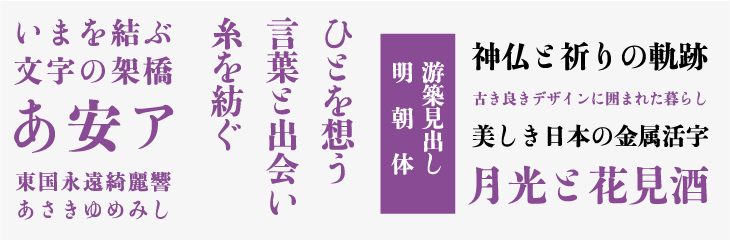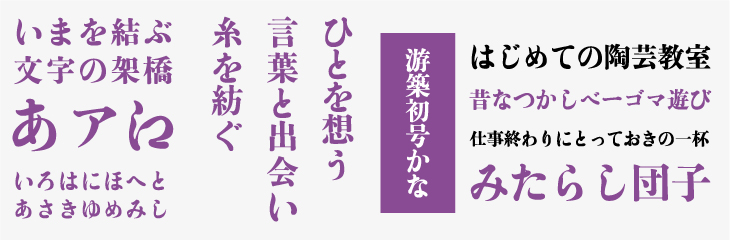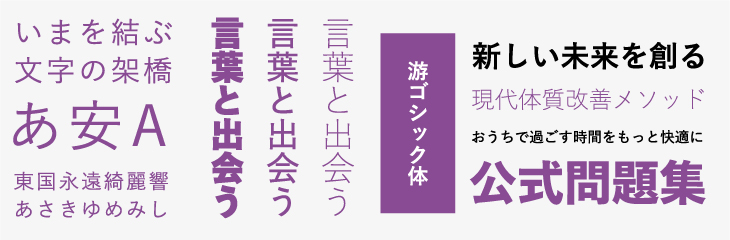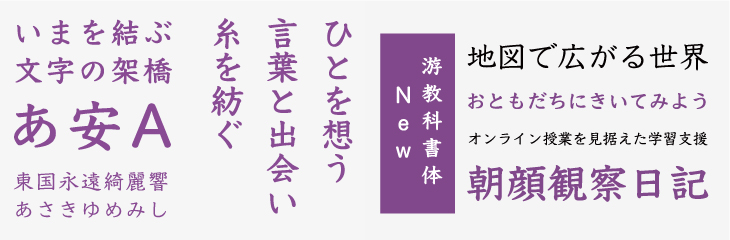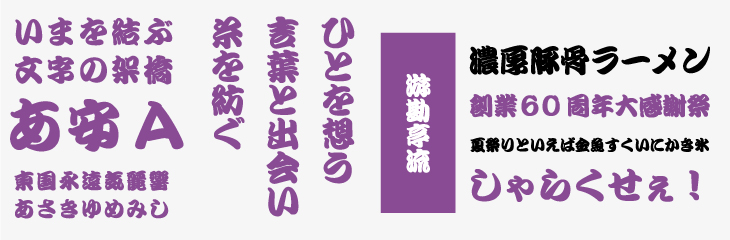
2020年秋よりMORISAWA PASSPORTに「游明朝体」など字游工房の全46書体を追加
モリサワは、子会社である字游工房がライセンスを保有するフォント「游明朝体」など全46書体を2020年秋にMORISAWA PASSPORTにて提供することを2020年9月4日に発表した。
長文組版での可読性を追求したフラッグシップ書体「游明朝体」や「游ゴシック体」をはじめ、大正時代の金属活字の雰囲気を持つ「游築見出し明朝体」、太くうねりのある筆文字を読みやすくアレンジした「游勘亭流」、東京書籍株式会社と共同開発された教科書体「游教科書体 New」と小学英語用欧文書体「JKHandwriting」のほか、情緒豊かな「游明朝体五号かな」「游明朝体36ポかな」「游築初号かな」「游ゴシック体初号かな」のかな書体を提供する。
新書体として、フェルトペンのメモ書きのような親しみやすい印象のペン字体「ぺんぱる」、中国晋代の碑文と日本の近代活字を復刻した柔らかなゴシック体「くれたけ銘石」、漫画の吹き出しや辞書の見出しなどで使用されるアンチック体にインクのにじみ加工を施した「秀英にじみアンチック」、UD黎ミンシリーズとの併記を目的として開発されたセリフ体「Lutes UD PE」が追加される。
また、「黎ミン」「新ゴ」「新丸ゴ」のAP版のほか、かな書体「秀英アンチック」と「秀英角ゴシック」の漢字を組み合わせた「秀英アンチック+」も追加され、人気書体の利便性がさらに高まる。
さらに、子会社である有限会社字游工房がライセンスを保有するフォントも追加。
長文組版での可読性を追求したフラッグシップ書体「游明朝体」や「游ゴシック体」をはじめ、大正時代の金属活字の雰囲気を持つ「游築見出し明朝体」、太くうねりのある筆文字を読みやすくアレンジした「游勘亭流」、東京書籍株式会社と共同開発された教科書体「游教科書体 New」と小学英語用欧文書体「JKHandwriting」のほか、情緒豊かな「游明朝体五号かな」「游明朝体36ポかな」「游築初号かな」「游ゴシック体初号かな」のかな書体など全46書体となる。
2020年秋MORISAWA PASSPORT収録:游明朝体
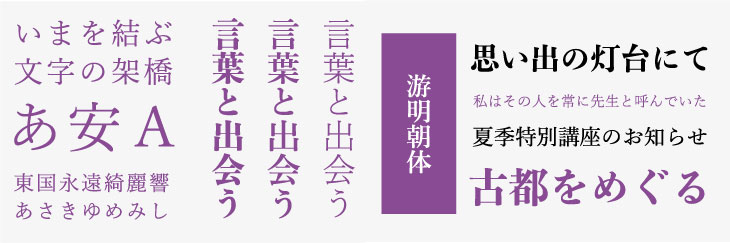
「時代小説が組めるような明朝体」をキーワードに開発された、落ち着きのある明朝体ファミリー。文字の空間が均一に見えるような設計、丸みのあるウロコや柔らかな曲線が、明るく品のある雰囲気を演出する。「游明朝体」は6つのウエイトで展開され、見出しに特化したBとEは他のウエイトとは骨格が異なりふところが狭く、引き締まったデザインになっている。
2020年秋MORISAWA PASSPORT収録:明朝体五号かな
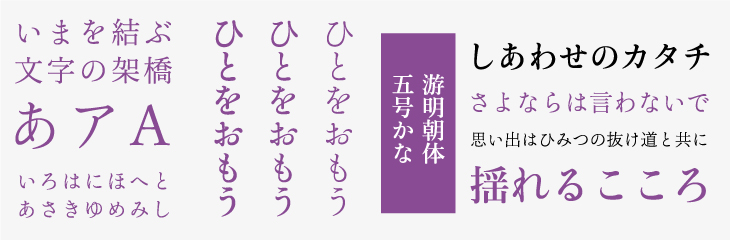
明治時代に制作された五号(本文向けサイズ)の金属活字をベースにつくられたかな書体。「游明朝体」の標準かなより字面が少し大きく、ゆったりとした柔和な線が特徴。「游明朝体」の漢字と組み合わせて使うことで、見出しや雑誌の本文を古典的で穏やかな印象に仕上げた。
2020年秋MORISAWA PASSPORT収録:游明朝体36ポかな
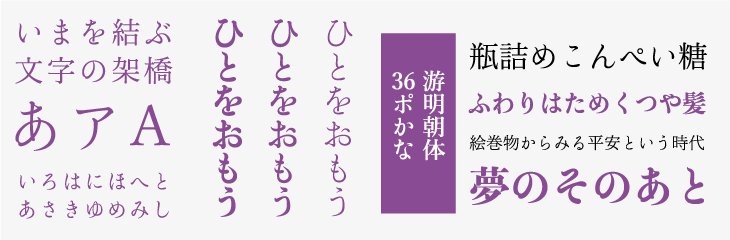
大正時代に制作された36ポイント(見出し向けサイズ)の金属活字をベースにデザインしたクラシカルなかな書体。